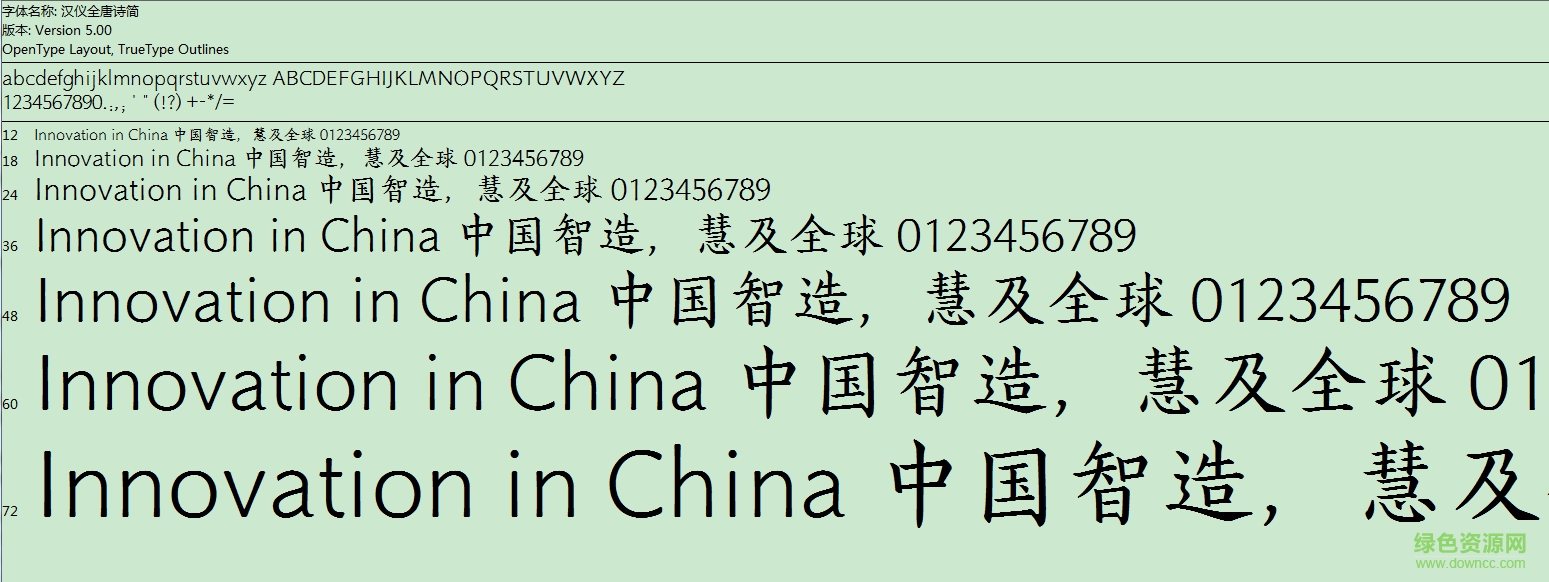
漢儀全唐詩簡體是一款非常好看的漢儀字體,這款字體字體工整,秀美不失力度,展現(xiàn)出一種優(yōu)雅的古風氣質(zhì),喜歡的朋友歡迎來綠色資源網(wǎng)下載使用!
漢儀全唐詩體是一款應(yīng)用于正文的簡體中文字體,字形略微偏長,中宮收緊,秀美圓潤,帶寫刻風格,體現(xiàn)高雅氣質(zhì)感,可廣泛應(yīng)用于正文標題、廣告設(shè)計、平面設(shè)計、印刷包裝等領(lǐng)域